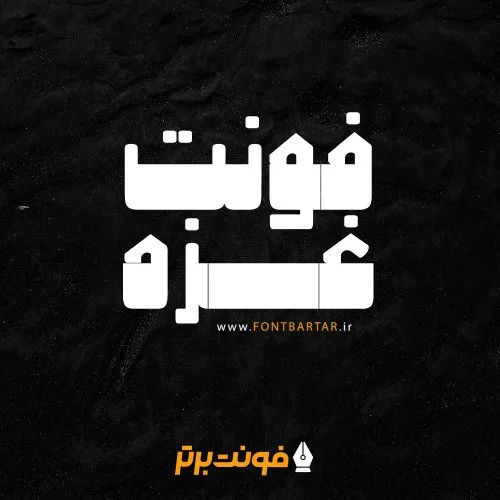
فونت فارسی غزه
فونت غزه از دسته فونت‌های فوق سنگین با بدنه‌ٔ قطور است. این سبک طراحی در حروفنگاری‌های دهه ۴۰ و ۵۰ مرسوم بوده و فونت‌های متعددی نیز در سال‌های اخیر به این سبک ساخته شده است. تفاوت اصلی فونت فارسی غزه با دیگر فونت‌های این دسته، هندسهٔ ساده و کنتراست ضخامت حروف است.